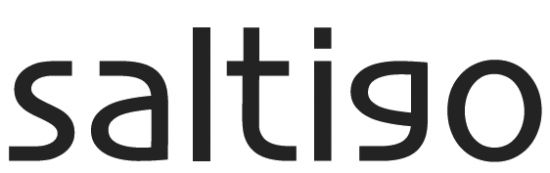
wer weiß was das für eine Schrift ist?
kennt jemand die Schrift? Kann man die kaufen oder ist das ne extra Entwicklung für das Logo? (siehe screenshot)
Identifont hab ich schon versucht...
Skia, würde ich mal tippen, aber das "g" ist handgemacht, der Rest evtl. auch leicht "angepasst".
Ja, echt übel, was? Und das bei einer Firma (Lanxess), die sich was Besseres hätte leisten können. Aber die haben auch Optima Light im Sub-Logo ...